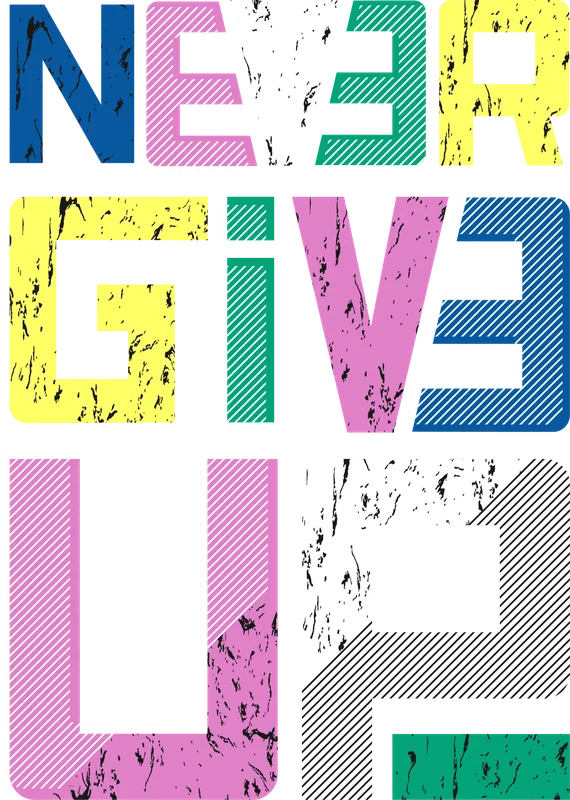
Đừng bao giờ bỏ cuộc - Font chữ retro năng động
Đừng bao giờ bỏ cuộc - Font chữ retro năng động — Thiết kế chữ 'Never Give Up' theo phong cách retro năng động, với hiệu ứng texture độc đáo. Tuyệt vời cho áo thun, poster, và nhiều sản phẩm in ấn khác. Có thể in bằng công nghệ DTF.
Trong hình có: chữ viết, typography
Phong cách: vintage · Cảm giác: mạnh mẽ
Tông màu chủ đạo: xanh dương, hồng, vàng, xanh lá